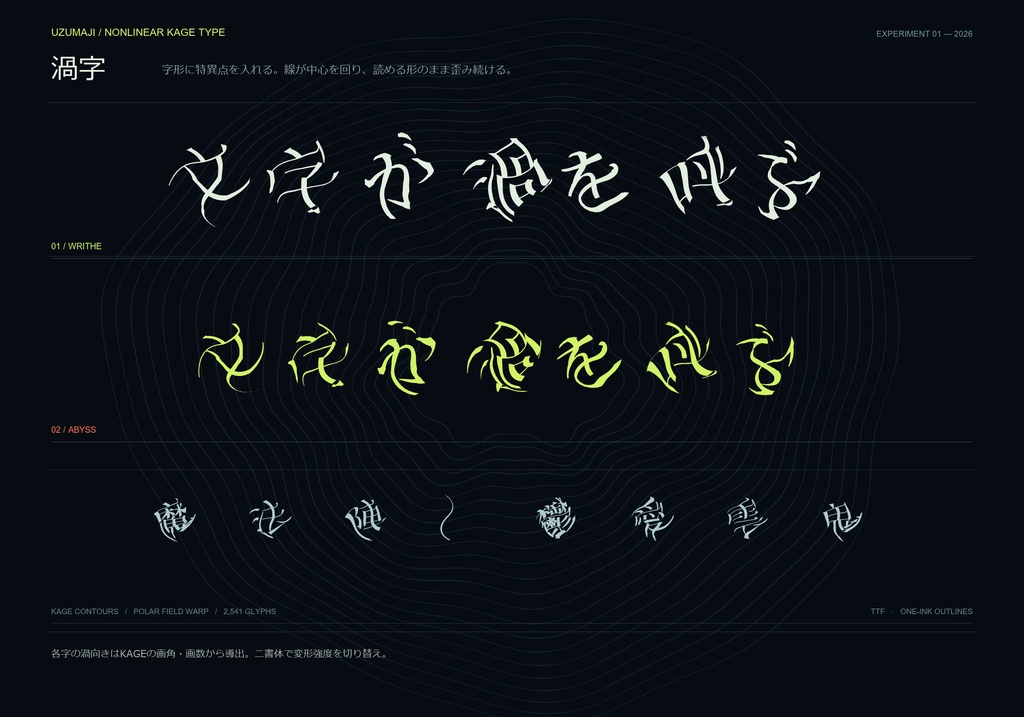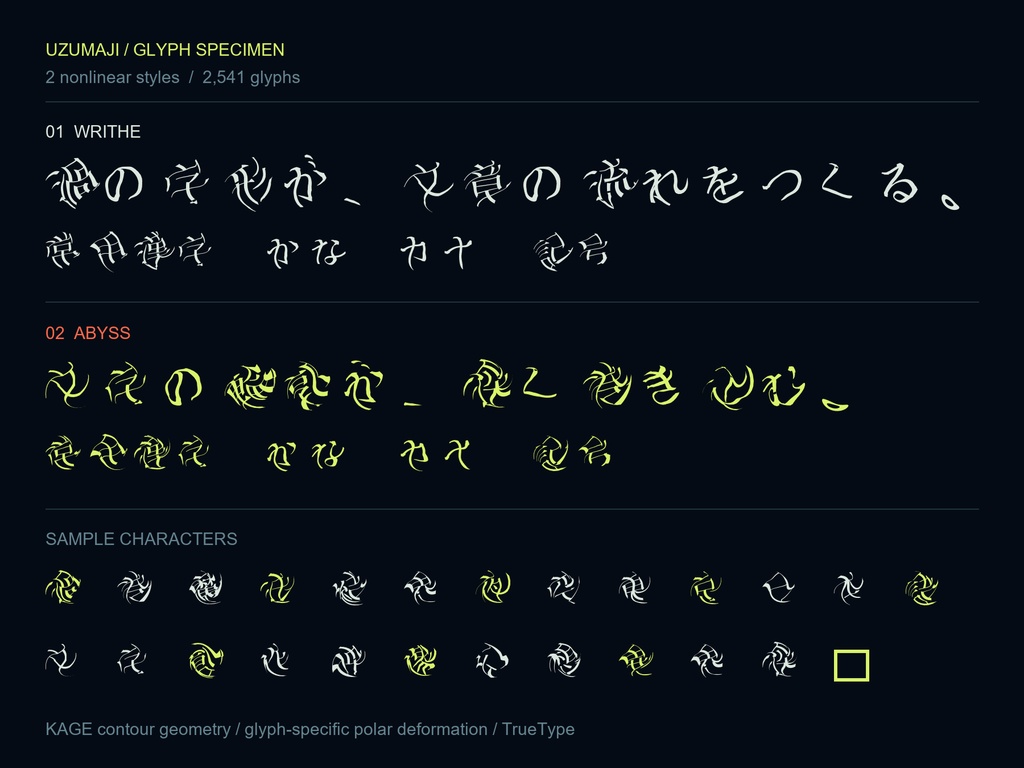
渦字 Uzumaji|渦巻く日本語ディスプレイフォント 2書体・常用漢字対応
文字の線が、字ごとに違う渦を描く。KAGEの輪郭を文字単位の極座標フィールドで変形した日本語ディスプレイフォント「渦字 / Uzumaji」です。 線は中心から外へ進むほどねじれ、画角や画数を手掛かりにした個別の変形をまといます。規則的な文字列が、渦・結界・異界の題字のように変貌します。 ■ 2つのスタイル ・Writhe:渦の輪郭を残しながら、文字の判読性を比較的保つスタイル ・Abyss:巻き込みを強くした、高密度で深いスタイル ■ 収録内容 常用漢字2,136字、ひらがな86字、カタカナ92字を含む合計2,541文字。TTF形式の2書体をZIPでお届けします。 ■ おすすめ用途 ロゴ、見出し、ゲーム・映像の題字、TRPGや同人誌の演出に。強い変形を含むため、小さな本文や長文には向きません。購入前に画像で字形をご確認ください。 ■ 仕様 TrueTypeアウトラインフォント。固定字形の静的フォントです。色や背景、見本画像のレイアウトはフォントに含まれません。 ■ 利用条件と出典 GlyphWiki由来の字形輪郭を加工しています。同梱のGLYPHWIKI_LICENSE.txtをご確認ください。元データのライセンス条件により商用利用・複製・再配布が許諾されています。本商品はパッケージと制作物への支援価格で頒布します。 制作: 2026 / 渦字 Uzumaji v1.0